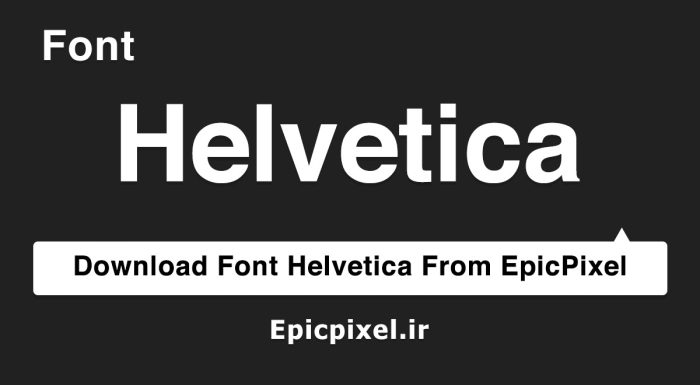
فونت Helvetica انگلیسی بدون شک یکی از شناختهشدهترین و پرکاربردترین فونتهای دنیاست. این فونت با طراحی ساده و خوانای خود، برای طراحان گرافیک، وبسایتها و پروژههای چاپی به گزینهای ایدهآل تبدیل شده است. اگر به دنبال دانلود رایگان فونت Helvetica انگلیسی هستید، در این مقاله همراه ما باشید تا ضمن معرفی این فونت کاربردی، بهترین منابع برای دانلود آن را به شما معرفی کنیم.
آشنایی با فونت Helvetica انگلیسی
فونت Helvetica در اواخر دهه ۱۹۵۰ میلادی توسط طراح سوئیسی، مکس میدینگ (Max Miedinger) طراحی شد. هدف از طراحی این فونت، ایجاد یک فونت خوانا و بدون تزئینات اضافی بود که بتواند جایگزینی مناسب برای فونتهای serif آن زمان باشد. Helvetica با الهام از فونت Akzidenz-Grotesk طراحی شد و توانست به سرعت جایگاه ویژهای در دنیای طراحی پیدا کند.
ویژگیهای کلیدی فونت Helvetica:
- سادگی و خوانایی: مهمترین ویژگی Helvetica، سادگی و خوانایی بالای آن است. حروف این فونت بدون تزئینات اضافی طراحی شدهاند که باعث میشود خواندن متنهای نوشتهشده با آن در اندازههای مختلف، آسان باشد.
- کاربری گسترده: Helvetica به دلیل سادگی و تطبیقپذیری بالا، در طیف وسیعی از پروژههای گرافیکی، از طراحی وبسایت و اپلیکیشن موبایل گرفته تا طراحی لوگو، بروشور و پوستر کاربرد دارد.
- حرفهای و مدرن: طراحی مدرن و مینیمالیستی Helvetica باعث میشود متون نوشتهشده با این فونت، ظاهری حرفهای و امروزی داشته باشند.
چرا از فونت Helvetica انگلیسی استفاده کنیم؟
همانطور که اشاره شد، Helvetica یک فونت همهکاره است که برای طیف وسیعی از پروژههای طراحی کاربرد دارد. در ادامه به برخی از دلایل اصلی استفاده از این فونت اشاره میکنیم:
دانلود- خوانایی بالا: خوانایی بالای Helvetica باعث میشود تا پیام شما به درستی به مخاطب منتقل شود. این ویژگی برای طراحی وبسایتها و اپلیکیشنهای موبایل که کاربران در معرض حجم زیادی از اطلاعات قرار میگیر بسیار مهم است.
- قابل اعتماد و حرفهای: Helvetica با طراحی مدرن و مینیمالیستی خود، حس اعتماد و حرفهای بودن را به مخاطب القا میکند. این ویژگی برای کسبوکارهایی که قصد دارند تصویری حرفهای از خود به نمایش بگذارند، بسیار مناسب است.
- تنوع وزنهها: فونت Helvetica در وزنهای مختلفی از لایت (Light) تا بلک (Black) ارائه میشود. این تنوع به شما امکان میدهد تا بر اساس نوع پروژه خود، وزن مناسب را انتخاب کنید.
نکات مهم در استفاده از فونت Helvetica انگلیسی
- استفاده از وزن مناسب: فونت Helvetica در وزنهای مختلفی ارائه میشود. انتخاب وزن مناسب فونت، به نوع پروژه شما بستگی دارد. برای مثال، برای متون چاپی مانند کتاب و مجله، بهتر است از وزنهای سنگینتر مانند Bold استفاده کنید.
کلام آخر
فونت Helvetica انگلیسی یک فونت همهکاره و پرکاربرد است که برای طیف وسیعی از پروژههای طراحی گرافیک و وبسایتها مناسب است. با دانلود رایگان فونتهای مشابه Helvetica از وبسایتهای معتبر، میتوانید از مزایای این فونت زیبا و خوانا در پروژههای خود بهرهمند شوید.